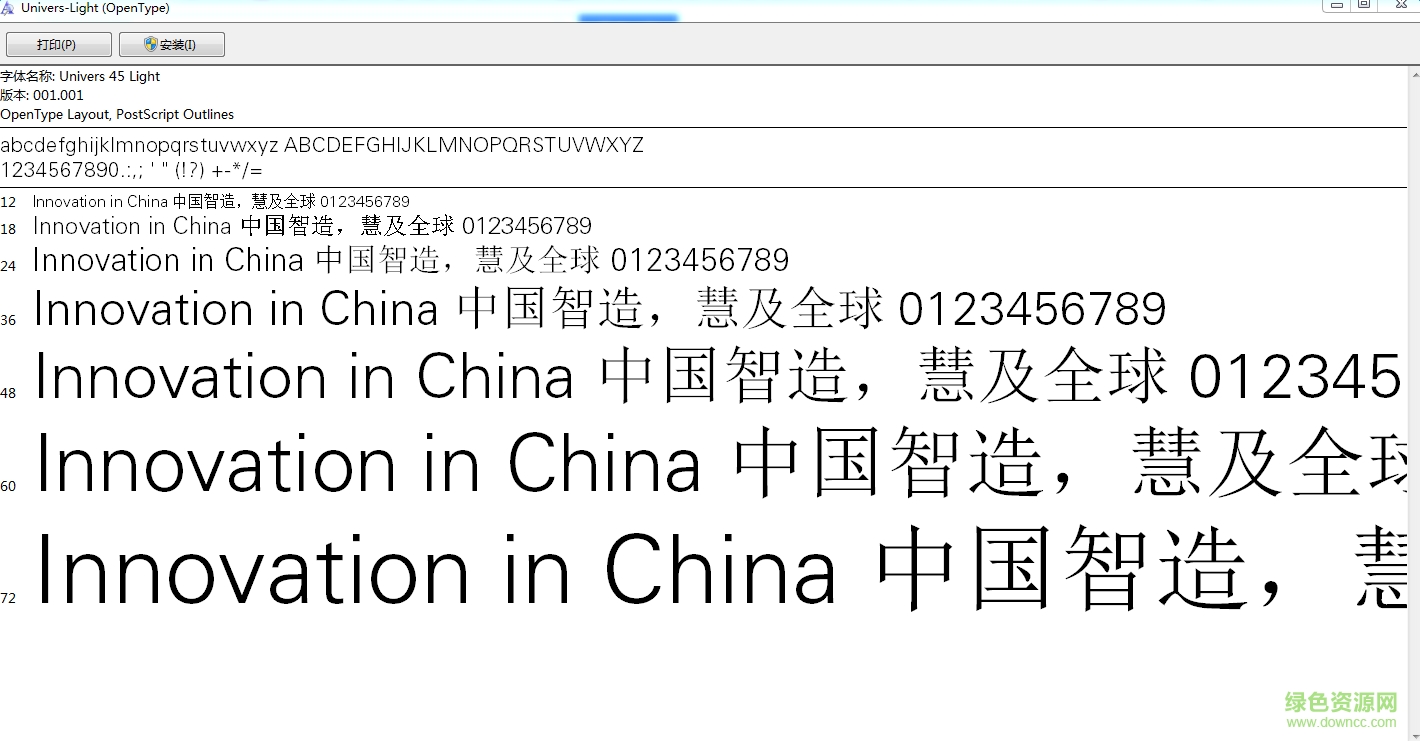
univers 45 light字體是一款實(shí)用性強(qiáng)的字體,該字體結(jié)構(gòu)平穩(wěn),字形秀氣,空隙均勻,引人注目,可適用于各類(lèi)文字排版,有需要者歡迎在綠色資源網(wǎng)下載!
univers light字體筆劃纖細(xì),布白均勻,閱讀效果好,印小字也清晰易讀,適合排各類(lèi)標(biāo)題及廣告設(shè)計(jì)。大家快來(lái)下載收藏吧!